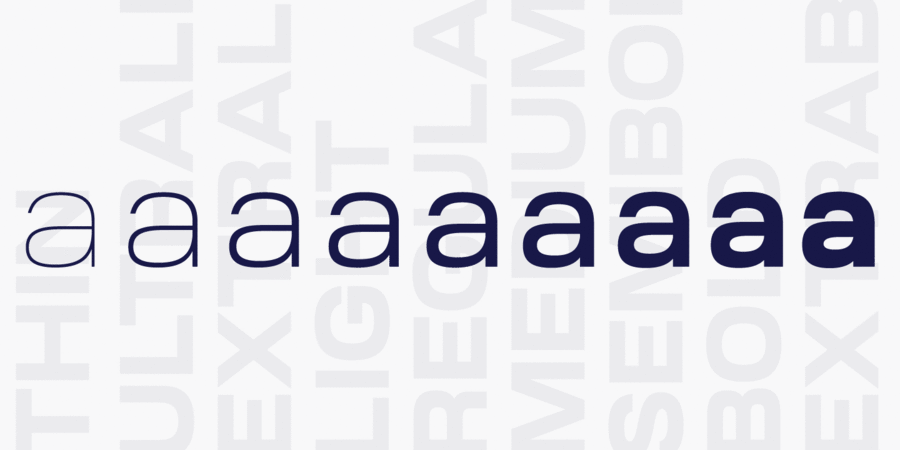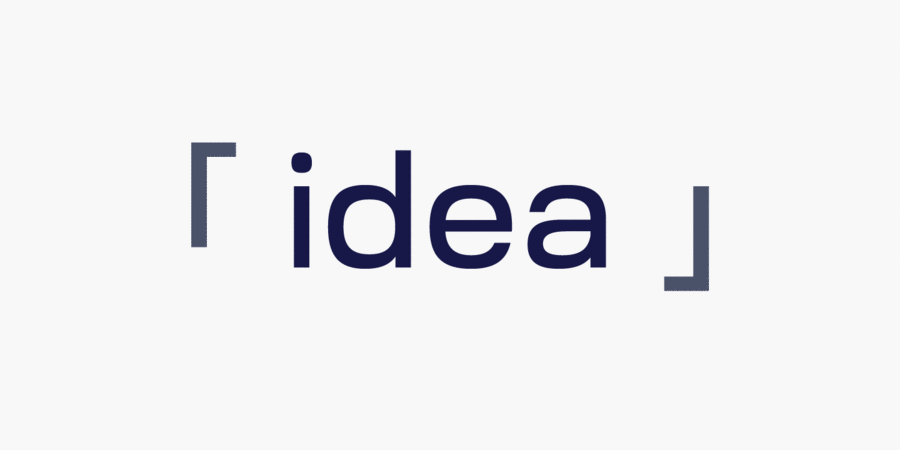
Опис гарнітури RuberoidГеометричний ґротеск зі зпрямленими овалами, що нагадує італійські шрифти 1950-х і 1960-х років, але він має значно більш круглі форми, щоб надати йому сучаснішого вигляду. Шрифт поставляється у 9 насиченостях із супутніми нахиденими накресленнями і підтримує латинку, гречку та кирилицю. Шрифт розробив Олег Ліщук у 2020 році.
Асоціації з сімейством шрифтів RuberoidОсобистість і характер гарнітури:
інженерний, точний, логічний, рівний, міський, якісний, західний, спокійний, сучасний, модний, холодний, тонкий, легкий, ясний, чистий, невагомий, прозорий, худий, гладенький, скляний, крихкий, футуристичний, дротяний, неоновий, лаконічний, мінімалістичний, автоматичний, космічний, діловий, серйозний, стабільний, статичний, стійкий, глобалізований, глобалістічний, технічний, креслярський, Простий, формальний, непомітний, впевнений, надійний, спортивний, важливий, переконливий, швидкий, рішучий, залізничний, гоночний, швидкісний, мужній, потужний, сильний, авторитетний, помітний, важкий, індустріальний, техногенний, крутий
прилад, гаджет, девайс, дизайн, креслення, чистота, гігієна, шампунь, технології, фантастика, космос, техніка, наука, інтернет, мобільний зв'язок, айтішник, айті, IT, інженер, архітектура, Місто, конструктор, медицина, бізнес, транспорт, аеропорт, метро, ліки, фінанси, астрономія, комп'ютерна гра, авто, автомобіль, автобус, паливо, спорт, залізниця, швидкість, ралі, залізо, комп'ютер, Локдаун, логістика, гонки, Доставка, верстат, машинобудування, промисловість, енергетика, електростанція, інструмент, мотор, двигун, телебачення, поліція, авіація, кіберспорт Гарнітура асоціюється з віком: